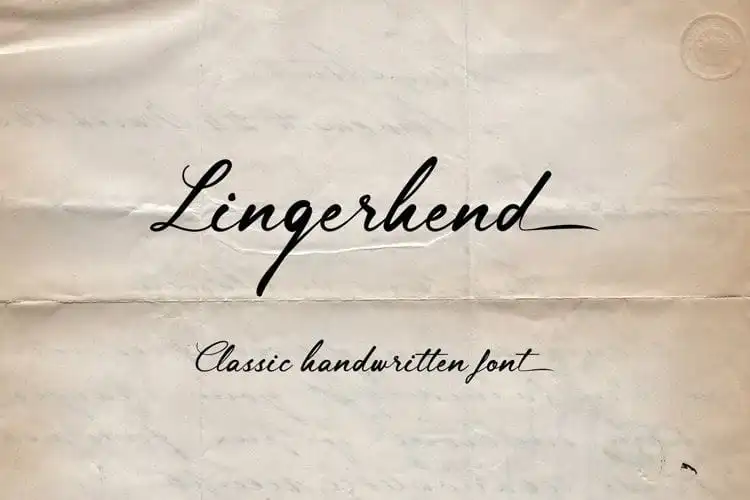
Lingerhend Handwritten Font – Download Grátis
A Lingerhend Handwritten Font é uma criação inovadora que une formas modernas e estilizadas com um toque contemporâneo, criando um efeito encantador para designers de projetos digitais. Fundada pelo designer de fontes chamado lemonthe, esta tipografia é uma versão clássica de uma script manual. É perfeitamente adequada para diversos usos, desde as embalagens de produtos até o design de postagem nas redes sociais e criação de materiais para festas e eventos, proporcionando um toque elegante e personalizado a qualquer projeto. Esta fonte é ideal para quem busca expressar uma verdadeira identidade visual moderna com uma aparição tradicional, tornando-a perfeita para uso em anúncios casais, papéis de sobremesa e em todas as suas criações visuais criativas que desejam um toque único.